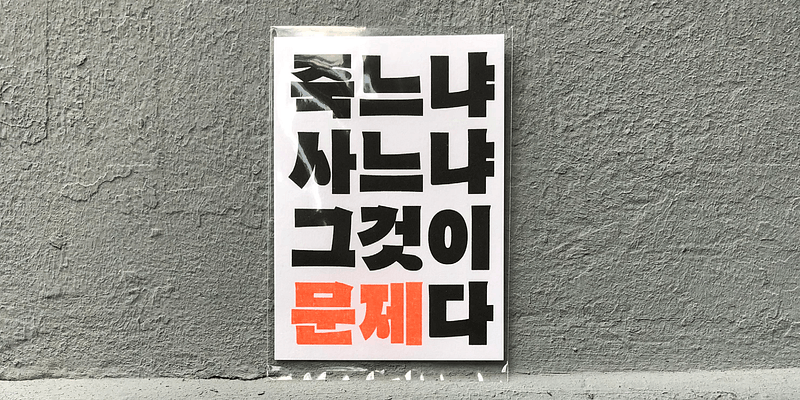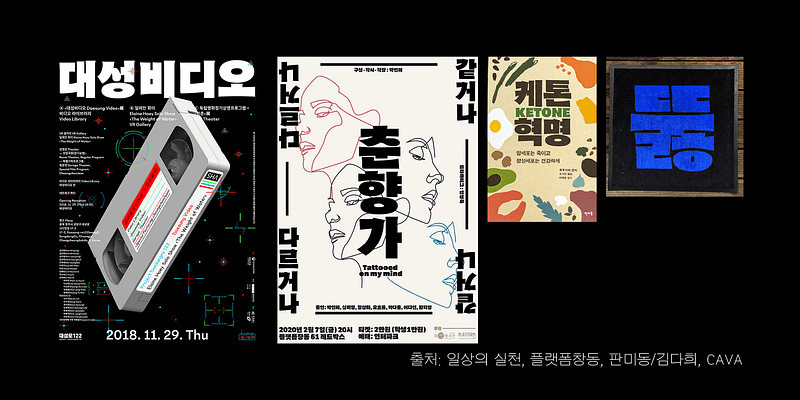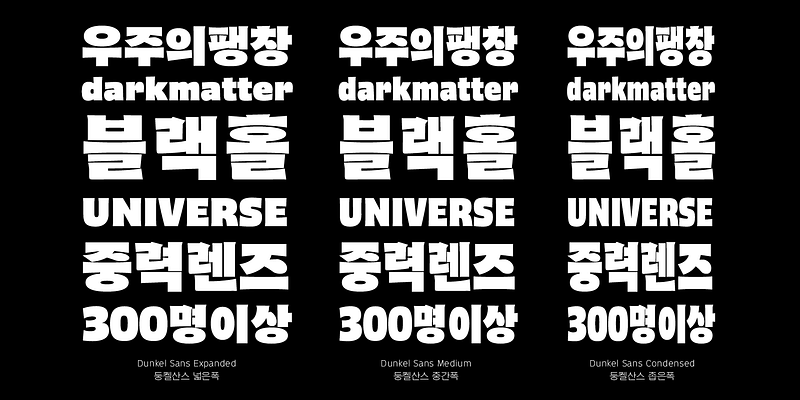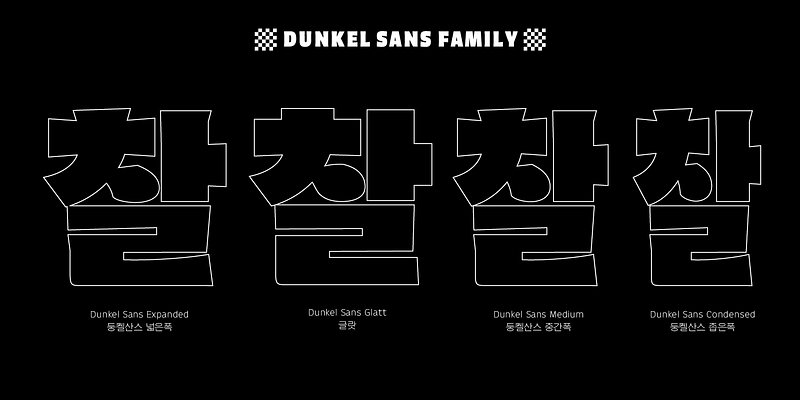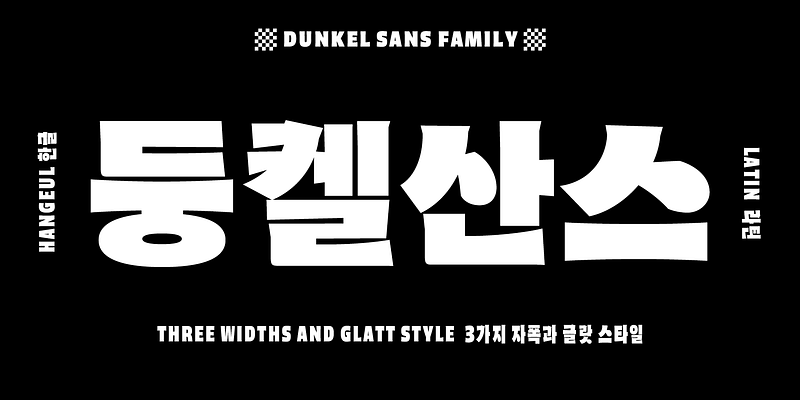
Dunkel Sans は、元気で重量感のあるディスプレイフォントで、ポスターや看板アプリケーションに激しい印象を残すのに最適です。Dunkel とはドイツ語で暗いという意味で、その名が示すとおり、超黒にデザインされています。
最初のインスピレーションは、1950 年代の手描きの韓国映画ポスターから得られました。その後、最初のデザインはダークサイドに押しやられ、ハングル書体での黒色の限界を探りました。Dunkel Sans は、重厚なインパクトでデザインにスパイスを加え、作品をユニークで力強いものにします。